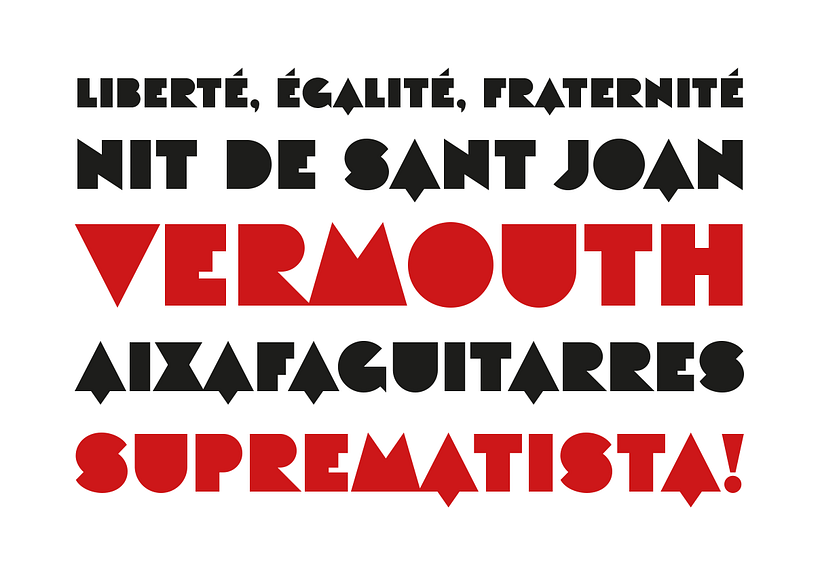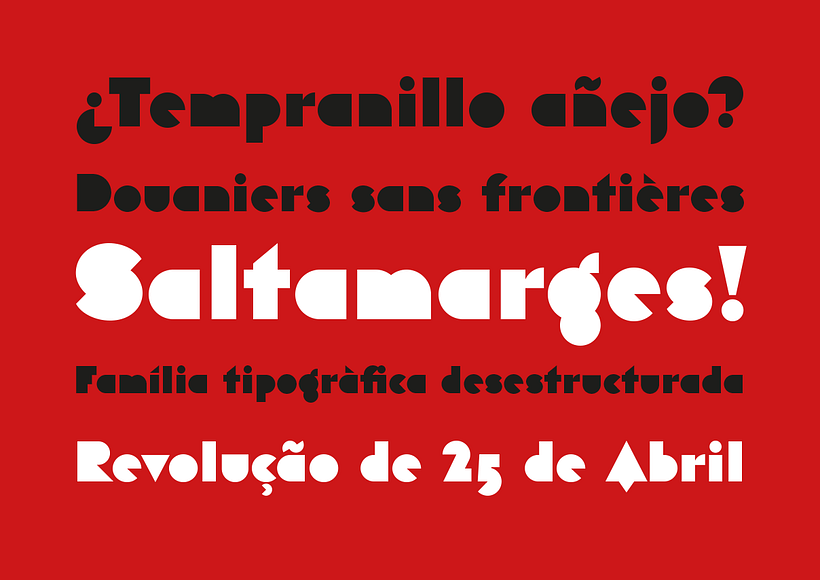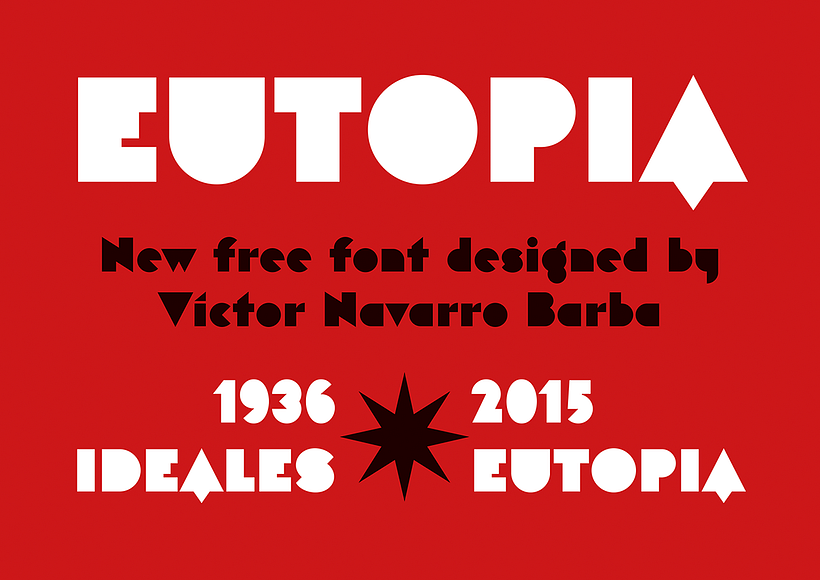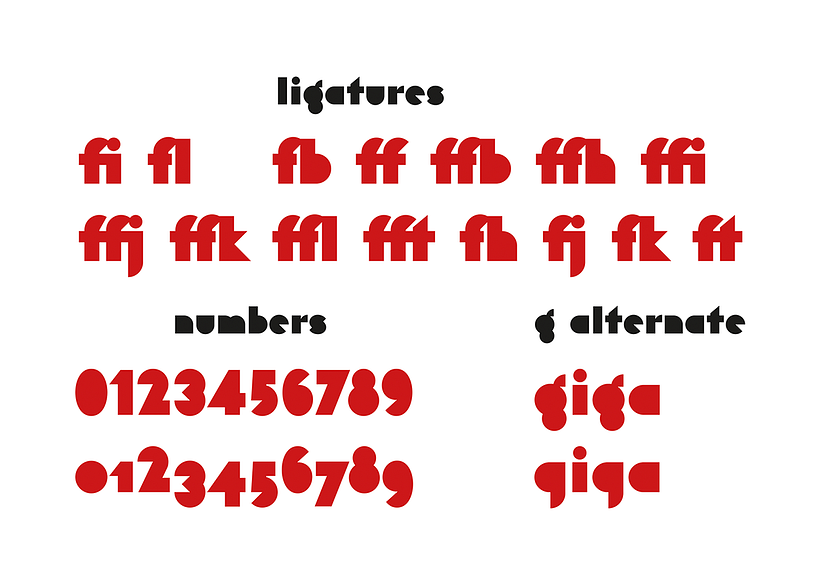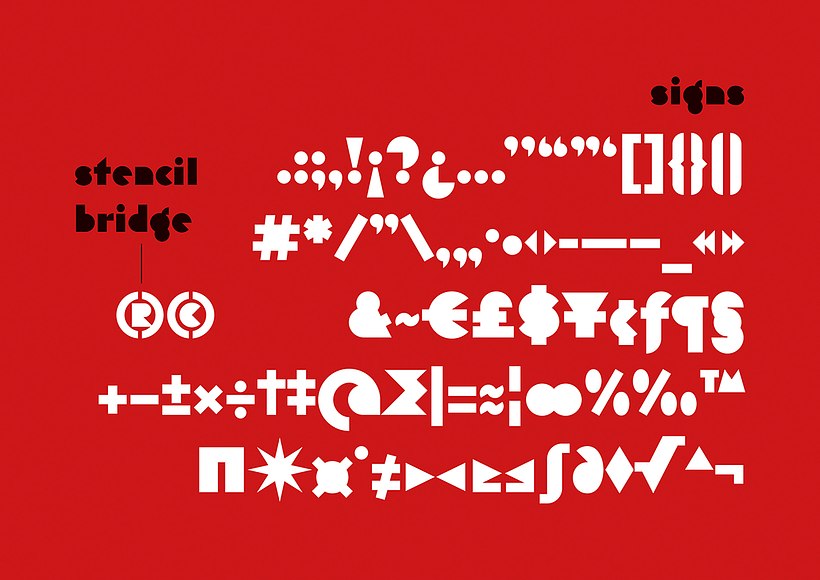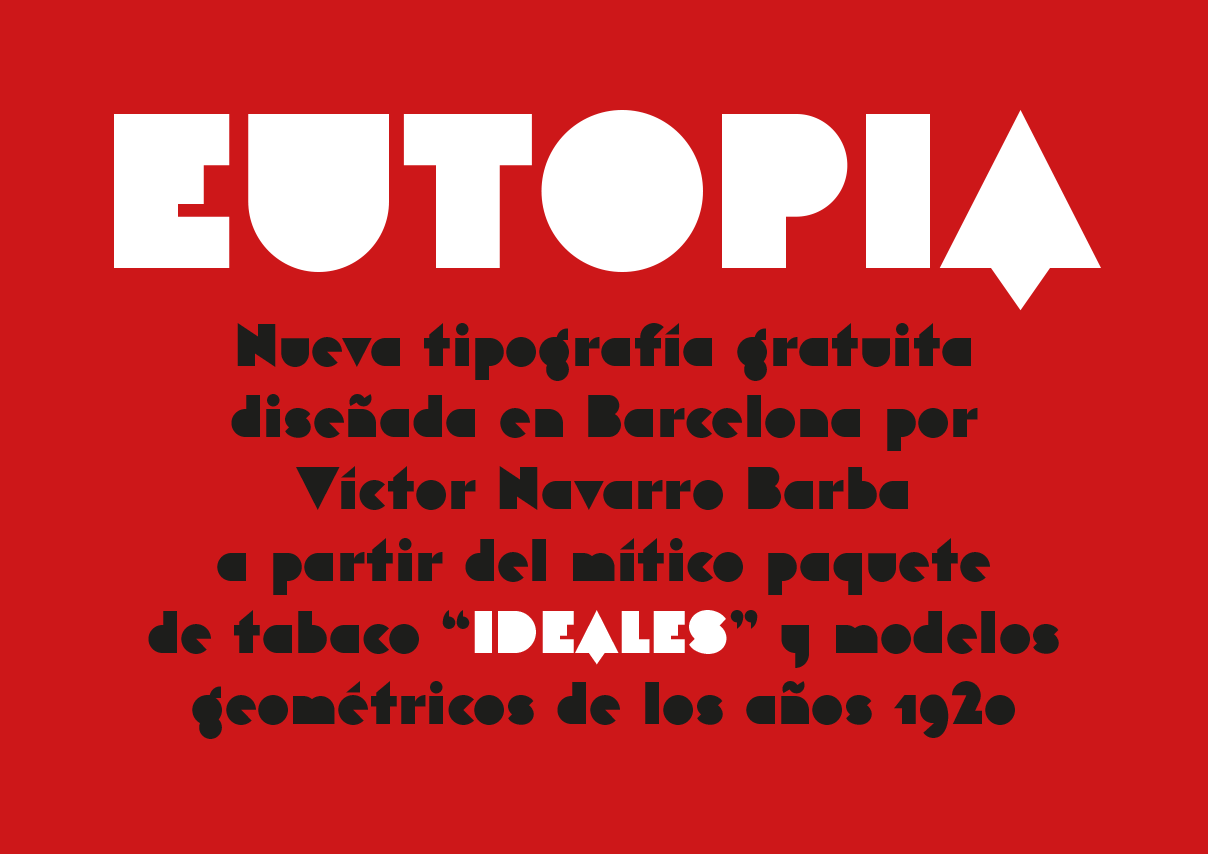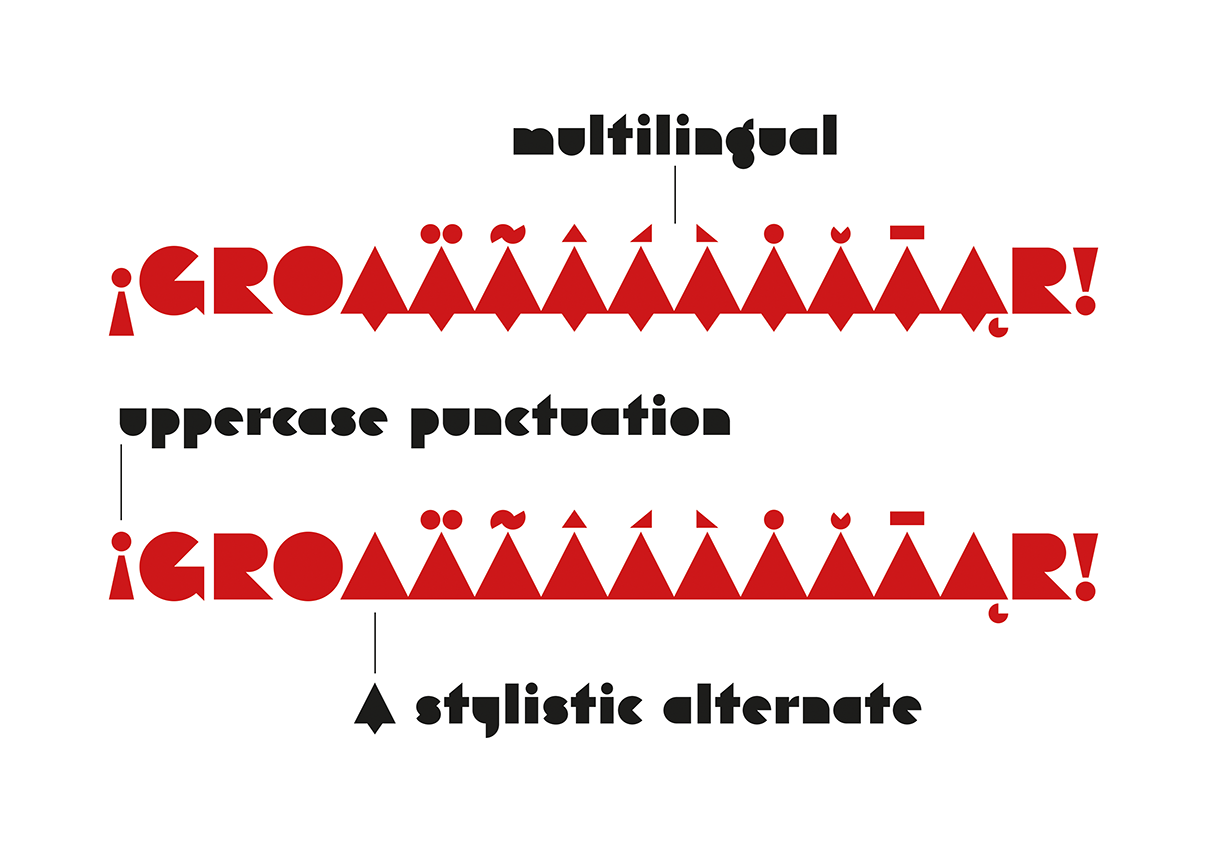
Eutopia, eine freie geometrische Schriftart
Eutopia, una tipografía geométrica gratuita
von Víctor Navarro Barba @tipofil
Inspiriert von den Buchstaben der legendären Tabakpackung „Ideales“ , die 1936 in Barcelona von Carlos Vives , dem Leiter des Grafikstudios der grafischen Industrie Rieusset, entworfen wurde. Wir haben auch andere geometrische Modelle aus den 1920er Jahren untersucht, darunter das 1928 in Amsterdam von Cornelis André Vlaanderen gezeichnete Alphabet, das höchstwahrscheinlich als Inspiration für die berühmte Tabakpackung diente.
Eutopia wurde mit dem Ziel entwickelt, die moderne grafische Kommunikation zu unterstützen. Zu diesem Zweck wurden fast 400 Glyphen entworfen und über 2.100 Kerning-Paare definiert. Zahlreiche diakritische Zeichen wurden für mehrsprachigen Einsatz in den meisten Sprachen mit lateinischem Alphabet vorbereitet. OpenType-Funktionen wurden genutzt, um alternative Buchstaben für „A“ und „g“, Ligaturen , Ziffern für Kleinbuchstaben und weitere typografische Verfeinerungen bereitzustellen.
Inspirada en las letras del mítico paquete de tabaco “Ideales”, diseñado en 1936 en Barcelona por Carlos Vives, jefe del estudio gráfico de la industria gráfica Rieusset. También hemos estudiado otros modelos geométricos de los años 1920, entre los que destaca el alfabeto dibujado en Amsterdam en 1928 por Cornelis André Vlaanderen, que muy probablemente sirvió de inspiración para el famoso paquete de tabaco.
Eutopia nace con la vocación de ser útil para las comunicaciones gráficas actuales, y para ello se han diseñado casi 400 glifos y se han definido más de 2.100 pares de kerning. Se han preparado múltiples signos diacríticos para su uso multilingüe en la mayoría de lenguas que utilizan el alfabeto latino. Se han aprovechado las funcionalidades de OpenType para disponer de caracteres alternativos de “A” y de “g”, ligaduras, cifras para minúsculas y otros refinamientos tipográficos.